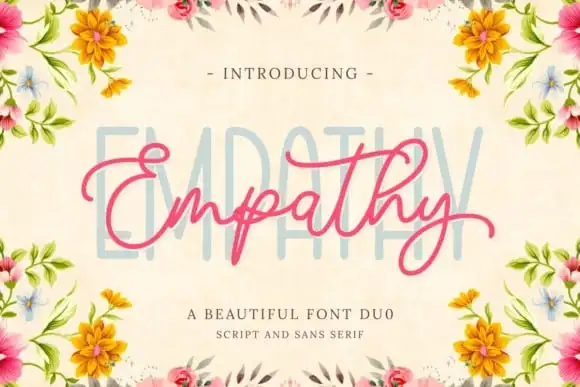
Empathy Handwritten Font – Download Grátis
A Empathy Handwritten Font é uma elegante fonte script criada com amor. Ela traz à sua produção design um toque decorativo único. Esta tipografia moderna e delicada é perfeita para aqueles que buscam um equilíbrio harmonioso entre a seriedade do tipo serifado e o charme encantador de uma fonte script. Uma das suas principais características é a combinação de uma linha levemente curiosa com um tipo sans-serif moderno, resultando em uma versão multifont que se adapta perfeitamente a diversos estilos. Agora imagine esta beautosa tipografia disponível para você personalizar qualquer projeto visual. Ela inclui alternativas e ligaturas especializadas para maximizar sua flexibilidade e impacto visual. Seja um design de revista, cartão de aniversário ou uma capa de livro de arte, a Empathy Handwritten Font estará sempre ao seu lado como um convidado especial. E com o PUA codificado, é simplesmente prático para acessar todos os detalhes decorativos desta fonte encantadora. Seja qual for seu próximo projeto visual, a Empathy Handwritten Font está aqui para torná-lo único e inovador.